Font chữ VNF là gì?
VNF (Vietnam Font) là một trong những dự án phông chữ lớn và uy tín tại Việt Nam, bao gồm hàng trăm bộ font nổi tiếng trên thế giới được việt hóa một cách chuyên nghiệp. Đặc điểm của dòng font VNF là sự đa dạng, từ các bộ phông Sans-serif hiện đại, Serif cổ điển đến các dòng Script nghệ thuật.
Ưu điểm lớn của bộ phông VNF là tính chuẩn xác về bảng mã Unicode và sự căn chỉnh Kerning dấu tiếng Việt, đảm bảo rằng khi bạn thiết kế các đoạn văn bản dài hay các tiêu đề quảng cáo, chữ viết vẫn giữ được sự cân đối và thẩm mỹ của bản gốc. In Viva đã tuyển chọn bộ font VNF có cấu trúc vector ổn định để phục vụ cho việc thiết kế và in ấn.
04 Ứng dụng font VNF trong thiết kế bao bì và in ấn quảng cáo
Sự đa dạng của bộ font VNF việt hóa để đáp ứng mọi yêu cầu thiết kế khắt khe của doanh nghiệp:
- Thiết kế logo đa ngành nghề: Từ tài chính ngân hàng dùng font Serif đến công ty công nghệ dùng font Sans-serif đều có thể tìm thấy mẫu chuẩn trong bộ VNF.
- Sản xuất hệ thống hộp quà Tết: Kết hợp các bộ Script VNF cho lời chúc và Sans-serif cho thông tin doanh nghiệp tạo nên sự hài hòa trên bao bì.
- In ấn sản phẩm tri ân khách hàng: Logo dùng font VNF in UV lên bình giữ nhiệt, sạc dự phòng hoặc sổ tay mang lại vẻ ngoài hiện đại và chuyên nghiệp.
- Thiết kế bộ nhận diện văn phòng: Từ danh thiếp, phong bì thư đến túi giấy đựng tài liệu đều được đồng bộ hóa phông chữ một cách tinh tế.
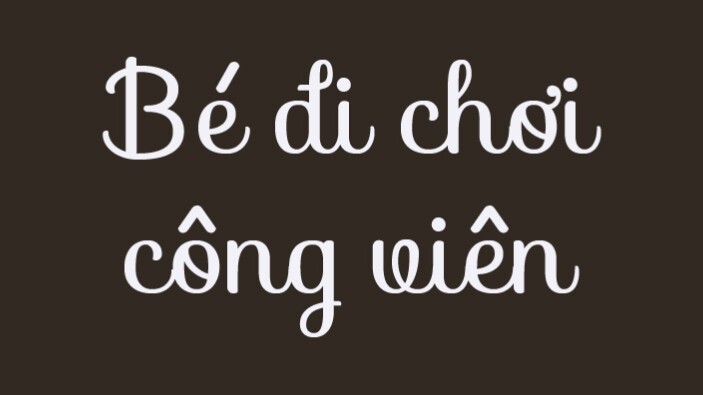
Sử dụng font chữ VNF cần lưu ý gì?
Để bộ phông chữ VNF phát huy tối đa hiệu quả thẩm mỹ trên thành phẩm in thực tế, designer cần lưu ý:
- Lựa chọn độ dày (Weight) phù hợp: Bộ VNF thường có đầy đủ từ Thin đến Black. Bạn nên chọn nét Medium hoặc Bold cho các tiêu đề trên túi giấy để tránh bị mất nét khi in.
- Tối ưu đường Path cho gia công bế nổi: Khi dập nổi logo dùng font VNF, hãy làm mượt đường path vector để khuôn bế không làm nhăm nhở mép giấy Ivory hay Couches cao cấp.
- Đồng bộ hệ màu CMYK: Đảm bảo màu sắc chữ in trên bao bì đúng với mã màu nhận diện thương hiệu của công ty.